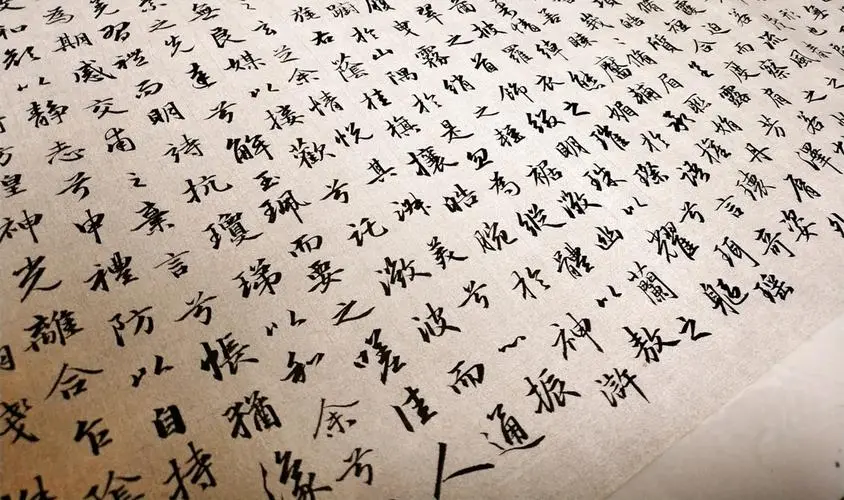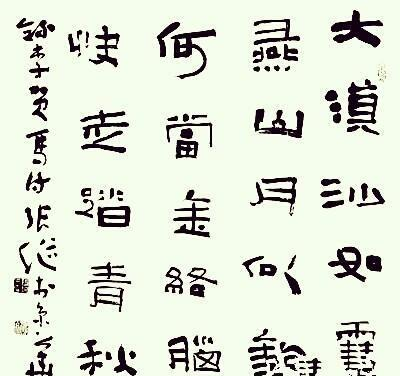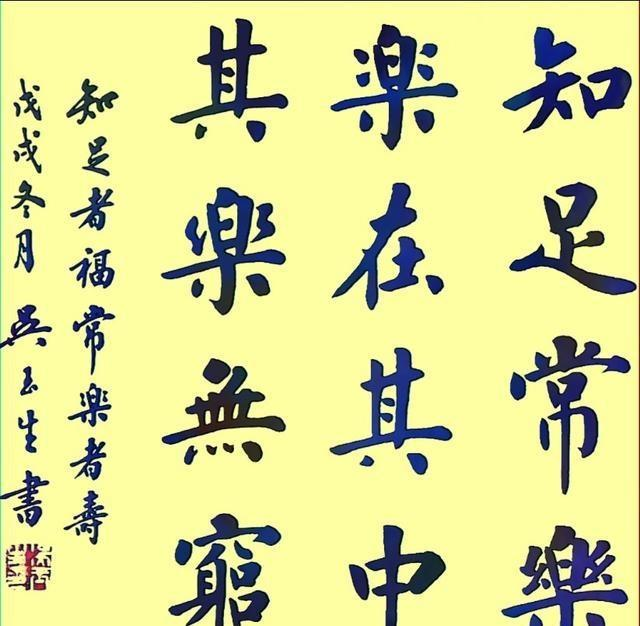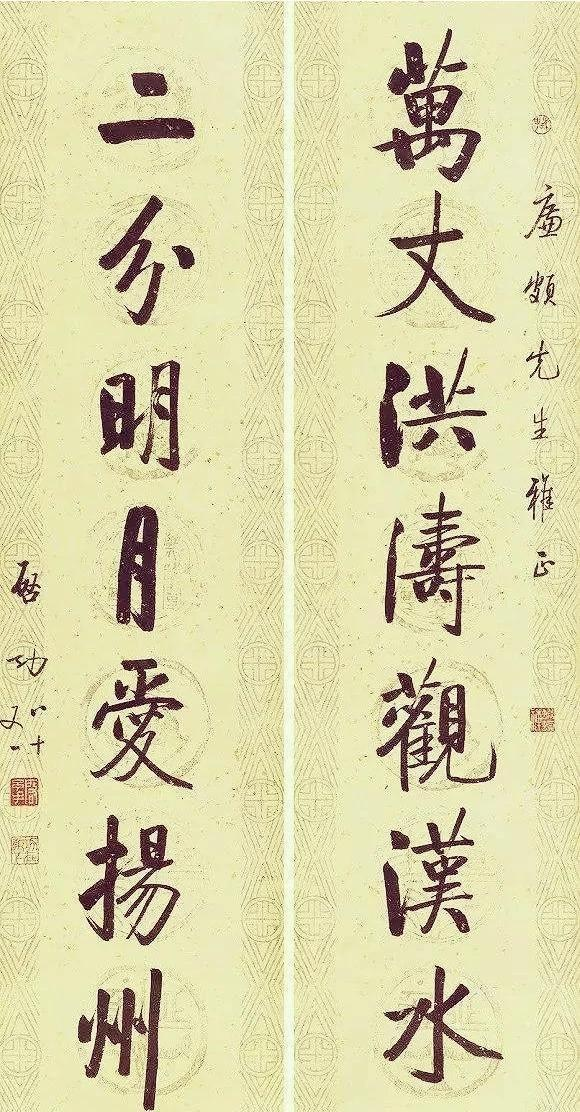
狼毫、羊毫和兼毫分别适合写哪种毛笔字体?
第一,写篆书,宜用兼毫毛笔。
第二,写隶书,宜用兼毫或羊毫。
第三,写草书,宜用羊毫毛笔。
第四,写楷书,宜用羊毫毛笔或兼毫毛笔。写小楷,宜用狼毫毛笔。
第五,写行书,宜用羊毫毛笔。
所谓的书者不择笔,就是无论写哪种书体,用什么毛笔都可以。张继老师写隶书时,就用过羊毫毛笔和狼毫毛笔,也用过兼毫毛笔,而且写的都很好。
启功先生写行书时,也用过狼毫毛笔。
所以说,什么事情都没绝对的。对于初学书法者来说,可择笔。对于有一定功底的书写者来,用哪种毛笔都可以。
兼毫毛笔不但可以写篆书和隶书,还可以写草书和行书,若不信,可试之。